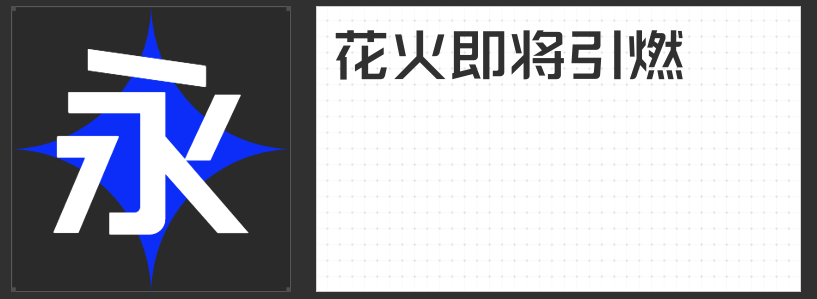
品牌标识的视觉利器:四款高辨识度字库字体推荐
在品牌视觉系统中,Logo设计是传递核心价值的第一张名片。字体的选择直接影响品牌气质的塑造——或刚劲有力,或温润包容,或灵动飘逸。以下四款专业字库字体,以独特的设计语言与结构美学,为高端Logo设计提供多元表达可能。
一、造字侠侠义简繁
这款字体以书法笔意重构现代字形,圆转笔画的运用打破传统黑体的机械感,勾挑牵丝的细节处理让文字产生动态韵律。其字形端正中暗含流动之势,粗细对比强烈的笔画既保留了狂草的洒脱,又通过重心平衡确保视觉稳定性。适用于文化创意、运动品牌等需要传递力量感与艺术性的领域,在简繁双版本的支持下,更可满足国际化品牌的多场景需求。
二、励字勇敢黑简 中黑
作为经典无衬线字体的进化版,其笔划粗壮如磐石,横竖笔画的均匀分布构建出强烈的视觉张力。通过钝化撇捺收笔的锐角,既保持了黑体的现代感,又提升了远距离识别的清晰度。这款字体尤其适合科技、金融等需要建立权威感的行业,在标题、导视系统等场景中能瞬间抓住受众视线。
三、励字志向黑简 大粗
圆体与黑体的创新融合,在笔画拐角处植入微弧过渡,使厚重字形摆脱呆板印象。外圆内方的结构设计既保证屏幕显示的清晰度,又通过字面框的适度扩张提升视觉冲击力。其特有的灵动气质,让教育、健康等领域的品牌标识在稳重中透出亲和力。
四、励字圆梦简 中黑
以直线与竖折笔画构建基础框架,却在起收笔处融入圆弧过渡,形成"方中有圆"的独特视觉语言。中宫松散的结构设计赋予文字呼吸感,外轮廓的规整性则确保了应用时的延展性。这款字体适合互联网、生活方式类品牌,既能传递简约现代的审美趣味,又通过细节处理避免流于冰冷。
在品牌同质化竞争加剧的今天,专业字体的设计价值愈发凸显。这四款字体通过结构创新与美学平衡,为Logo设计提供了超越常规的视觉解决方案,助力品牌在信息洪流中建立独特记忆点。